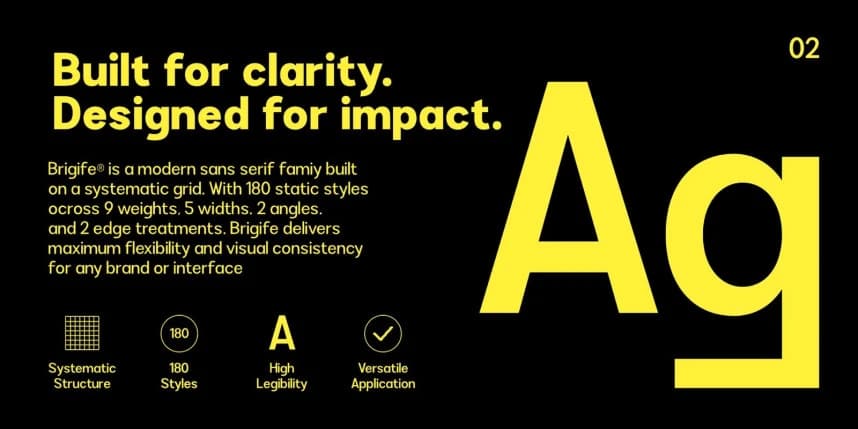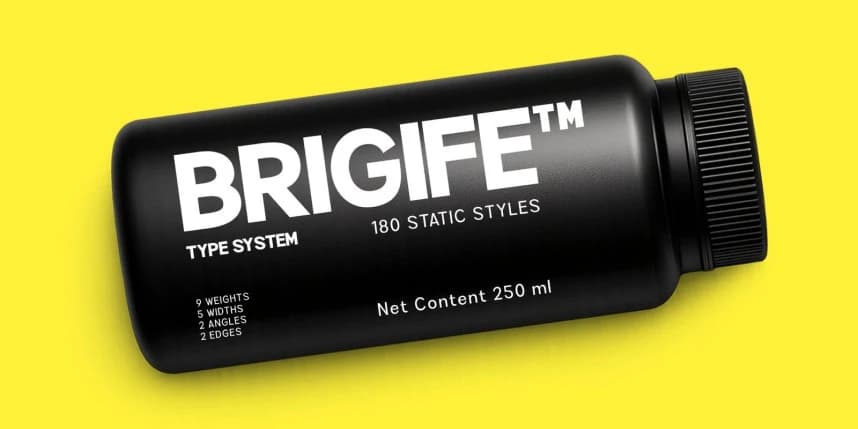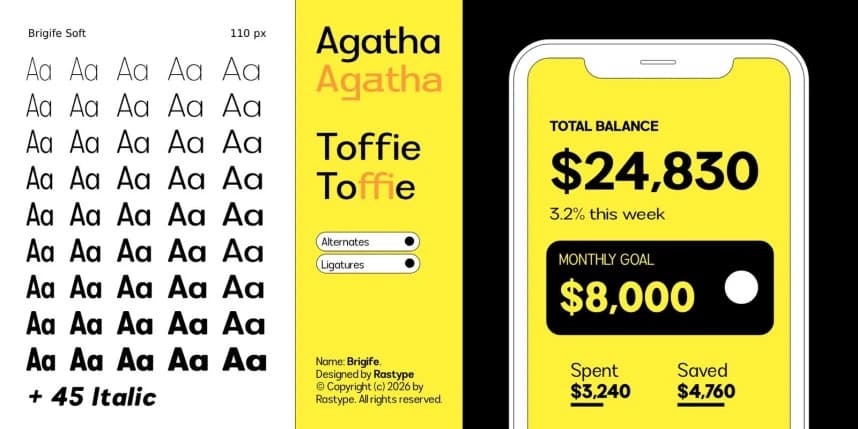
Brigife Yazı Tipi
Brigife Font, güçlü bir görsel varlığa ve çok yönlü bir karaktere sahip olacak şekilde tasarlanmış cesur ve çağdaş bir sans-serif yazı tipidir. Keskin geometrik kenarları ince yumuşak eğrilerle dengeleyerek modern ve erişilebilir bir ton yaratır.
Brigife Font, güçlü görsel varlığı ve çok yönlü karakteriyle tasarlanmış, kalın ve çağdaş bir sans-serif yazı tipidir. Keskin geometrik kenarları ince yumuşak eğrilerle dengeler ve böylece modern ama erişilebilir bir hava yaratır.